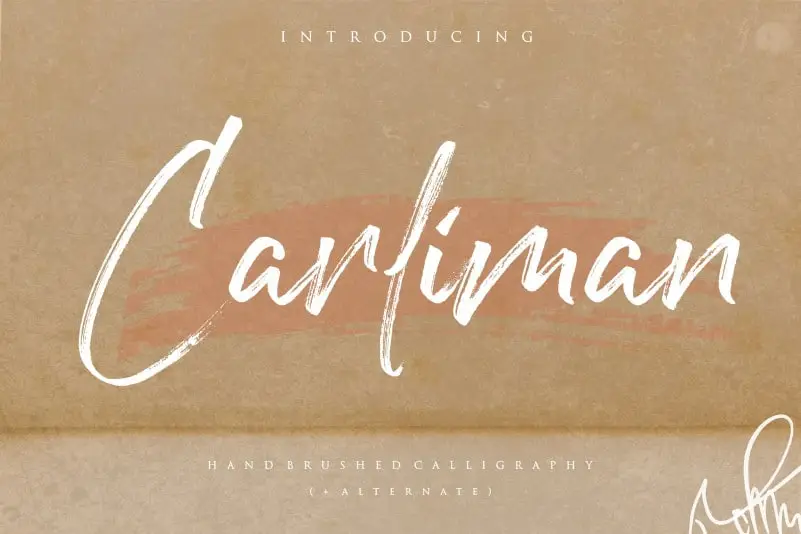
Carliman Handbrushed Calligraphy Font – Download Grátis
A fonte Carliman Handbrushed Calligraphy Font é perfeita para diversas aplicações criativas do design. Com seu charme delicado e linhas suaves, esta fonte se destaca especialmente para projetos de embalagens de produto, identidade visual de marcas (branding), revistas, mídias sociais, eventos como casamentos e até mesmo para expressar frases sobre o fundo. Seja em sua forma original ou personalizada, a Carliman Handbrushed Calligraphy é uma escolha inteligente para quem busca um toque artesanal e elegante em seus projetos visuais. Com seu design cuidadosamente elaborado e acabamento suave, essa fonte irá tornar qualquer projeto mais único e autêntico.